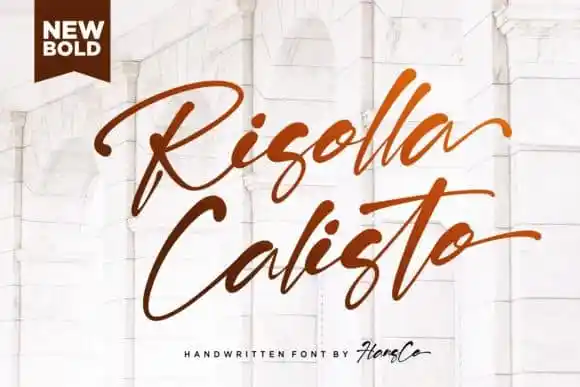
Risolla Calisto Script Font
Risolla Calisto Script é uma elegante fonte de estilo script que traz um toque nostálgico ao seu design. Esta fonte foi criada pelo talentoso designer HansCo, e tem sido adorada por designers do mundo todo por sua dinâmica e sofisticação. Suas linhas delicadas e detalhes meticulosamente trabalhados fazem dela uma escolha perfeita para aqueles buscando um toque vintage em qualquer projeto design. Com aplicabilidades vastas, que vão de cabeçalhos a marcações, Risolla Calisto Script é certamente garantida a adicionar uma dose mágica ao seu próximo projeto gráfico. Seja você designer de logotipos, publicidade ou editor de imagens, esta fonte vai trazer um toque único e sofisticado que deixará seu trabalho destoando da concorrência. Descubra por si mesmo o encanto desta fonte única do 99designs.